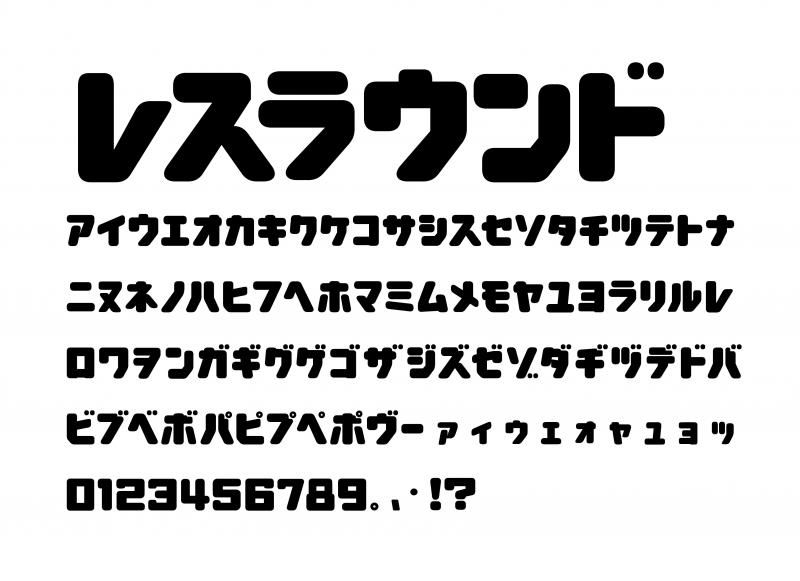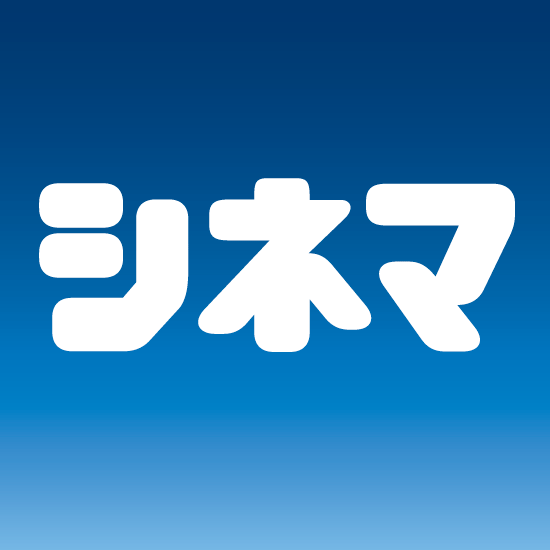
レスラウンド|Chiba Design|和文・欧文・デザイン書体のダウンロード販売|フォントファクトリー
商用利用可能なオリジナルフォントです。Open Type・ 2バイト・カタカナのみ。アウトライン化可能。レスラーフォントの角を丸めたフォント。可愛い場面を演出したい時にお使いください。ロゴの作成などに便利です。
レスラウンド